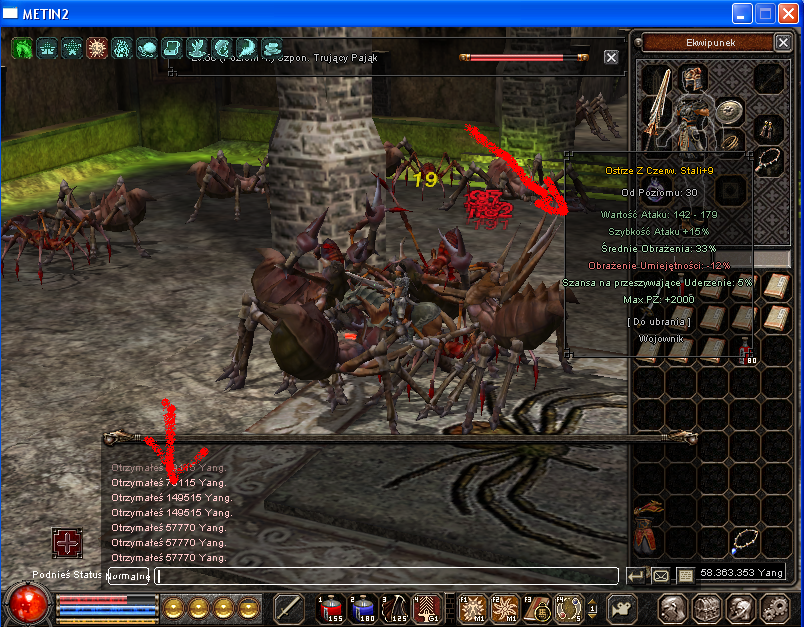
Czcionka Metin2
Witam dzis przedstawie wam czcionke jaką zrobilem na metin2
Odrazu powiem ze nie wiem czy to jakies odkrycie ale udalo mi sie zrobic taka czcionke na metin2
NIe chce narazie robic tuta dlatego bo nie wiem czy jest to tego warte
Jesli bedzie trzeba napisze tuta jak to zrobic, narazie piszcie co o Tym sadzicie
A co do tematu nic on nie wprowadza w tworzenie serweru, ani "nie prosi" o pomoc, więc się zastanawiam, czy w ogóle dobry dział wybrałeś.
Przeczytaj uwaznie "
Odrazu powiem ze nie wiem czy to jakies odkrycie ale udalo mi sie zrobic taka czcionke na metin2
NIe chce narazie robic tuta dlatego bo nie wiem czy jest to tego warte"
Myślę że to tylko zwiększone odstępy między liniami. Nie jest to nowa czcionka, a nawet nie poprawia to gry ( r+n wygląda dalej jak m
więc uważam że nie wnosi to nic do gry....